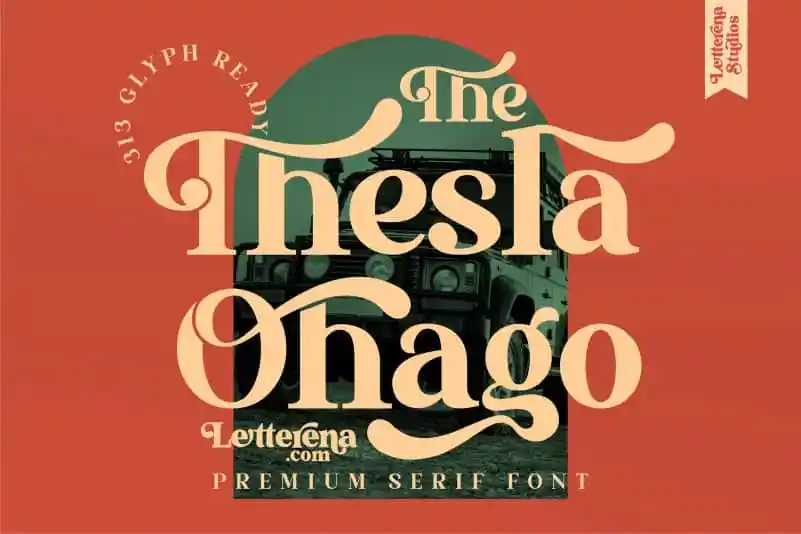
The Thesla Ohago Serif Font – Download Grátis
A The Thesla Ohago Serif Font é uma elegante escolha para qualquer projeto que exija um toque refinado e sofisticado. Conhecida por ser perfeitamente adaptável a várias necessidades, esta serif font está ideal para criações como logotipos, projetos de marca, designs de mobília, embalagens de produtos, taças, cartazes, sacolas de viagem, camisetas, capas de livros, convites e cartões de visita, cartões de agradecimento, etiquetas, fotografia, marcas d’água e eventos especiais. Ela é perfeita para qualquer projeto que busque um toque luxuoso e graciosamente estilizado. Conheça The Thesla Ohago Serif Font, uma fonte elegante da Letterena.